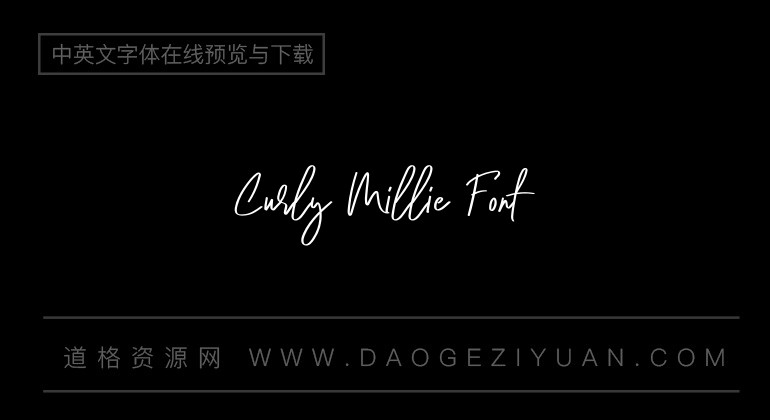
Curly Millie Font
Curly Millie Font 是一种手写字体,它具有浪漫、温馨、充满个性的特点。它的字母有着明显的连笔和弯曲,线条充满活力和动感,并且可以用于设计卡片、海报、包装等多种用途。 Curly Millie Font 字体包括大写字母、小写字母、数字和标点符号,可以免费下载使用。
Curly Millie Font是一款非常不错的手写艺术字体,具有很好的视觉感,适合于文化类的宣传设计、商业类品牌的广告和产品包装设计以及个性化文字排版等较多场景。